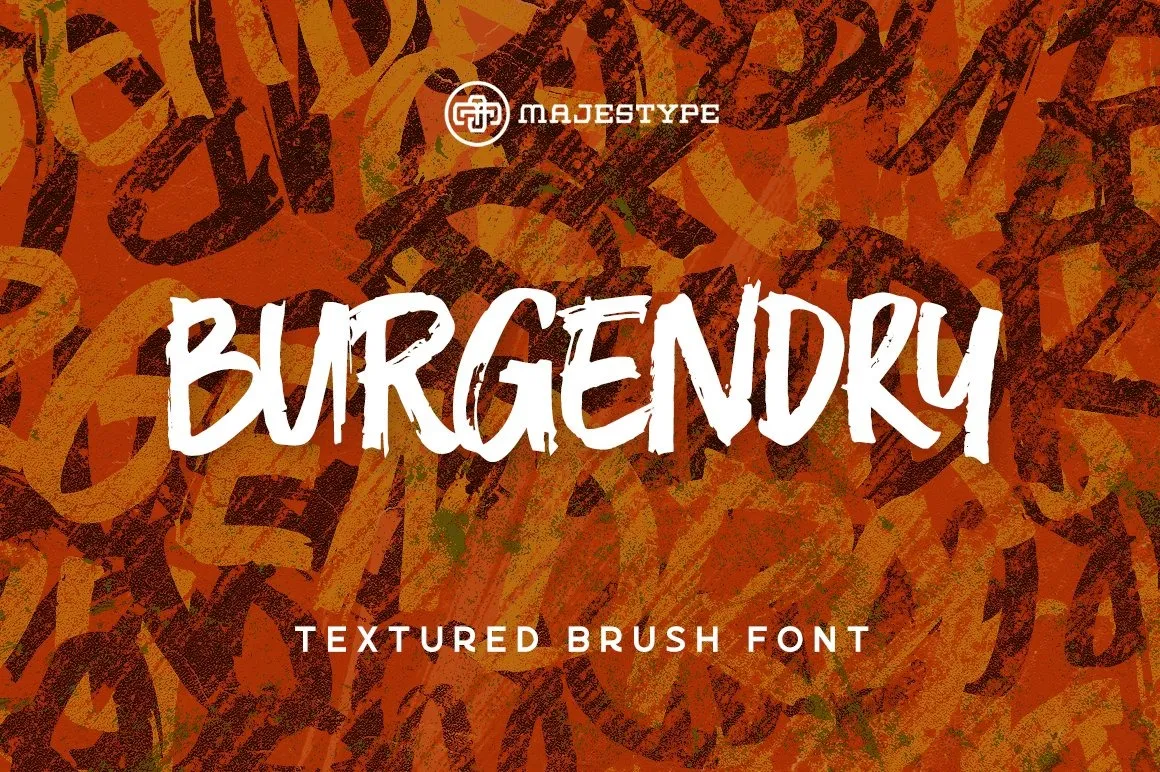
A Burgendry Font é uma escolha perfeita para quem busca personalidade e elegância em seu design. Ela surgiu do cruzamento entre a essência do script e a simplicidade de um traço feito por um pincel cuidadosamente impresso na folha de papel. Esta fonte tem características únicas, com uma característica orgânica que contrasta perfeitamente com sua aparência casual e assertiva. O designer da Burgendry, 99designs, produziu esta fonte para oferecer versões padrão e inclinadas, proporcionando um toque diferente em qualquer projeto. Seja para criar logotipos inovadores ou incorporar elementos distintivos em designs digitais, a Burgendry é uma escolha inteligente que trará seu trabalho para o próximo nível. Este script font combina a estética tradicional dos scripts com a frescura de um traço manual, criando assim um design único e autêntico.